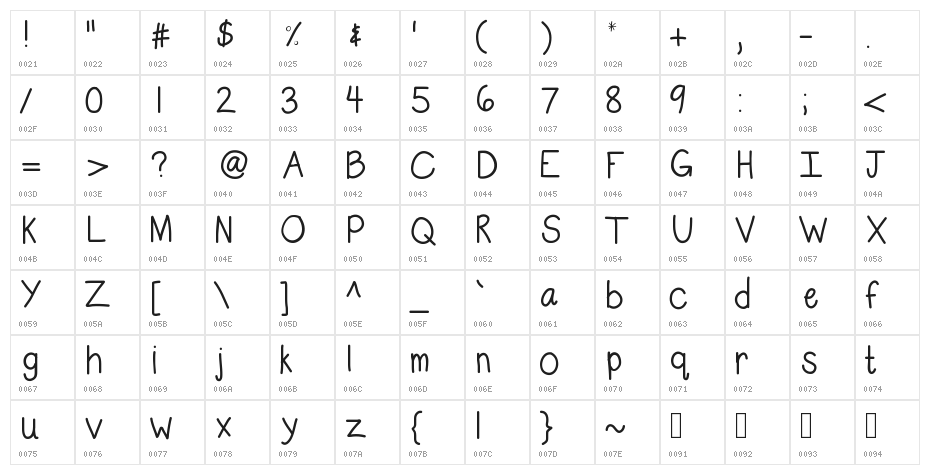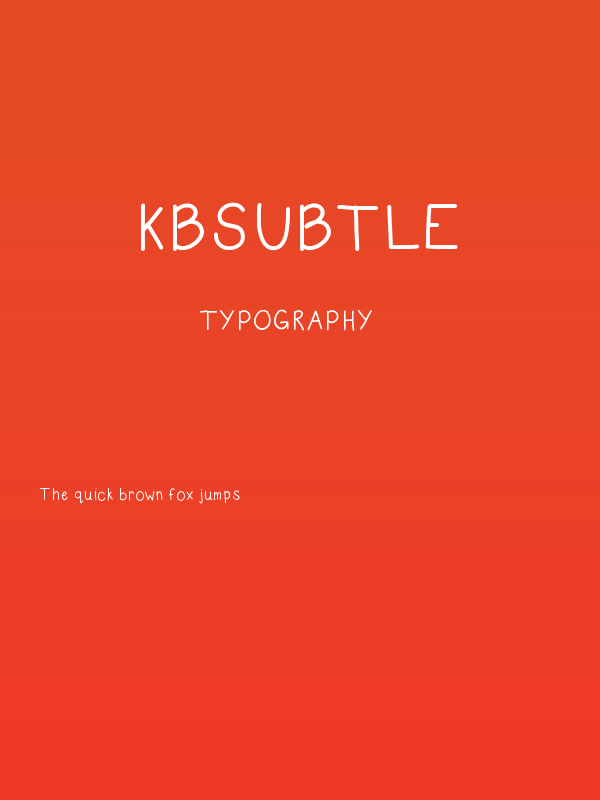
KBSubtle Font
Fonts by Khrys Bosland
| Gesamtstil | Casual |
| Anwendungsfall | Headlines, Informal text, Branding |
| Vorgeschlagene Projekte | Ideal for children's books, greeting cards, casual invitations, and playful branding. |